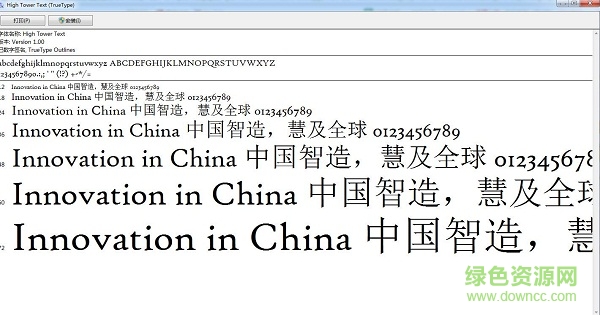
high tower text 字體
high tower text字體是一款襯線字體,細(xì)節(jié)處理細(xì)膩,粗細(xì)過渡緩和,結(jié)構(gòu)規(guī)范,實用性強(qiáng),可以用于報章雜志的內(nèi)文排版中,需要的朋友快來下載吧!
襯線字體介紹
擁有Serif的字體,一般都可以稱做Serif字體。Serif中文有翻譯作“襯線”或“線腳”的,起源類似于中國宋體字中橫筆的三角造型。古代羅馬文字的書寫是用扁平的筆,而我們現(xiàn)在看到的Serif也是在實際書寫過程中自然形成的。
襯線字體特征
Serif的造型各異,可以說是判斷Serif字體中各個細(xì)分類別的最重要參考造型之一。
非常古老,可以追溯到古羅馬時期的石柱銘文。它風(fēng)格古典、正式,具有歷史傳統(tǒng)和意義。